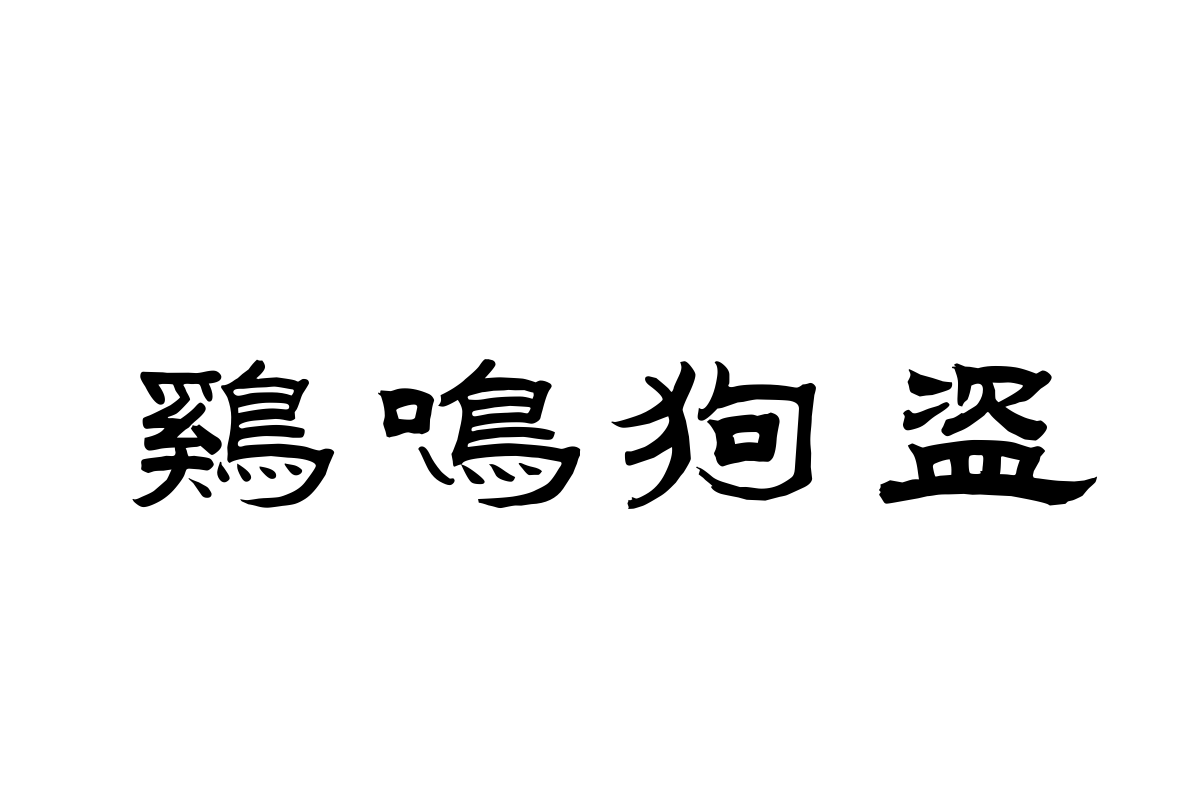
汉仪范笑歌隶书繁体是一种具有深厚文化底蕴的书法字体,它源于古代汉仪范的隶书风格。这种字体的特点是笔画流畅,结构严谨,线条粗细适中,既有隶书的古朴典雅,又有楷书的清晰易读。
汉仪范笑歌隶书繁体在字形上采用了传统的隶书结构,但又不是完全模仿古隶,而是在保持隶书特点的基础上进行了创新。它的笔画粗细变化丰富,既有隶书的粗犷,又有楷书的细腻,使得整个字体既有古典的韵味,又不失现代感。
此外,汉仪范笑歌隶书繁体还注重字体的平衡和协调,使得整个字体看起来既庄重又和谐。它的字体大小适中,既不过于夸张也不过于简单,适合各种场合使用。
总的来说,汉仪范笑歌隶书繁体是一种具有独特魅力的书法字体,它融合了传统与现代的元素,既有古典的韵味,又不失现代感,是书法艺术中的一种独特表达方式。